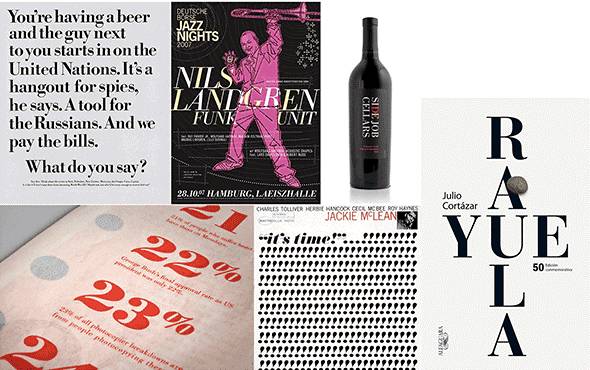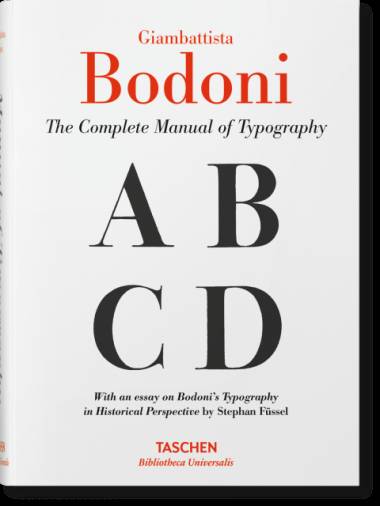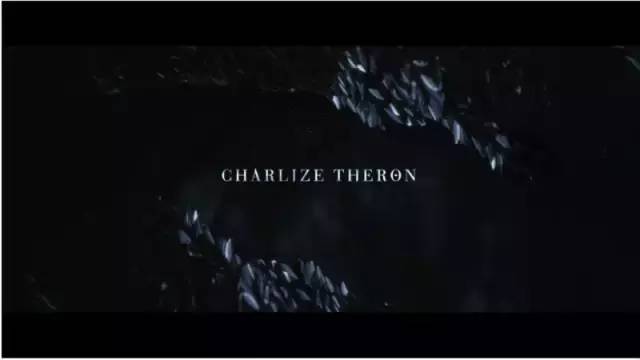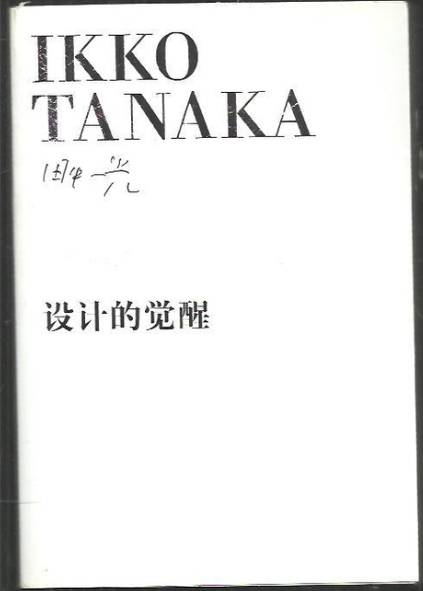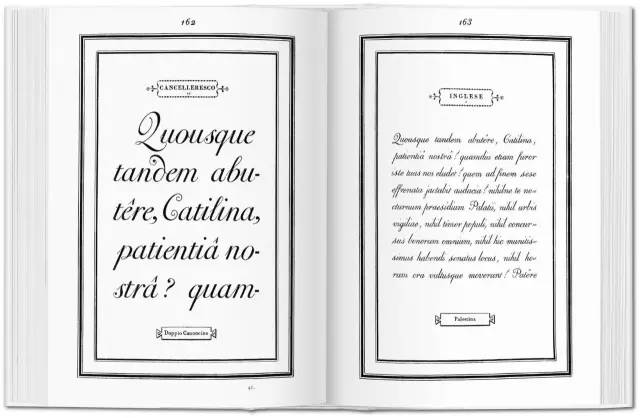
字体之美 | Bodoni字体,平面上的王者印刷
{{tag.name}}法国作家伏尔泰曾说:“文字是声音的画像”,作为一项视觉元素,文字比单纯意义上的图形、色彩更具有说服力和表现力。
在现代广告设计中,文字表现出的作用是非常重要的。广告中的文字不但能够作为信息传播的载体,还可以成为广告画面中的主体图形元素。
通过这个主体形象,不但可以对消费者展示其广告商品的自身性格,而且也可以体现出广告的文化内涵。
好的文字设计离不开字体的选择,无论是汉字字体还是字母字体都一样。网络发达的今天,随处可以下载的字体包,让我们眼花缭乱。
时间能够沉淀一切,好的字体也不例外。打开字体包,看到一个个的文字、字母,如果你只是因为某种字体好看而选择它,这样的选择似乎太轻。其实每一个好的字体背后都有其发展历史,有很多被我们忽略的故事,当你知道了这些字体背后的故事,回过头来看这些字体,也许你会看到不一样的东西。
在标题、广告上,我们经常能看到一种优雅浪漫的字体。在电影《白雪公主(与猎人)》中,导演也选择了这种字体并做了变形,他们在柔美字体的笔锋、转角、笔画交叉以及一些细节的地方加入硬朗的边缘。这就是Bodoni字体
【《白雪公主与猎人》Bodoni字体设计】
关于Bodoni字体的诞生,要从1740年意大利西北部的萨尔佐说起,那年我们的主人公金姆巴堤斯塔•波多尼(Giovanni Battista Bodoni)出生了。受印刷技术工人的父亲的影响,波多尼从小便接触印刷,十八岁时便离家到罗马教廷(教堂附设印刷厂)内当学徒。由于波多尼个性开朗,在厂内很有人缘,印刷厂主管路格里十分喜欢他,教了他许多印刷技术。在这儿,教宗希古斯兹斯五世所铸造的东方语文活字一直被荒废著不用。路格里要波多尼氏把这些活字再翻造一批。由于这次的工作经验,使他对制造活字和外国语文发生了浓厚的兴趣。
1766年,波多尼已经习得相当不错的技术,于是他离开罗马想到英国寻求发展。正当他要出发去英国时,一项工作改变了他的一生。巴尔曼的公爵费南度想设立一个印刷厂,希望波多尼到印刷厂工作,他接受了这份工作,职位是主管,此时波多尼才二十八岁。在印刷厂,波多尼负责印刷巴尔曼宫廷需要的印刷品以及费南度个人的印刷物(他是个艺术爱好者)。
波多尼的印刷厂也逐渐成为观光胜地。英国著名农业学家亚瑟·杨格在《意大利纪行》中记载著:“(1789年12月9日)下午,前往有名的波多尼印刷厂。波多尼将多数精美的印刷品展示在眼前。他的活字似乎足以凌驾巴黎的狄托氏(Didot)之上。他们两人的作风相彷,简直像为了节省纸张似的,字印得十分密集。《塔夫内与克洛耶》、《阿敏达》都印得相当精美。这些作品可以算是意大利印刷的代表,我买下后者。”
1790年以后,波多尼在巴尔曼宫廷的地位大为改善,原因是教廷驻西班牙公使准备在当地设立印刷厂以印制古典作品,邀请波多尼前往主持。此后,波多尼的印刷厂规模扩大了,而且拥有更大的自由。波多尼不仅印刷了意大利文、希腊文、拉丁文的书,更扩大到法文、俄文、德文和英文的书籍。
这时,波多尼的名声已渐渐传播到各地,所谓“王之印刷人,印刷人之王”便足以说明他的地位。不仅西班牙国王赏赐奖金,教宗也亲自颁奖给他;巴尔曼市为他铸造纪念牌,拿破伦也赏予奖金……。
一生致力于出版制作精美限量版艺术图书的著名出版商佛朗哥·玛丽亚·里奇曾说:“我清楚地记得是在1963年帕尔马的图书馆,我发现了一本古老的印刷手册,上面用的是波多尼字体,美得无以附加。于是一年后,我成立了自己的出版社,用优雅的波多尼字体印刷书籍,然后还出过一本用我自己首字母命名!
波多尼的工作大约可分两期。前期是使用旧有字体或过渡期活字的时代,这时候也大量使用装饰花纹。他显然受到法国很深的影响。1771年的活字样本簿标题页的花边就是模仿富尼尔所设计的作品。法国风味的印刷物在波多尼早期作品中随处可见,代表作有阿那克里翁的《抒情诗》等杰作。
后期所印制的书在整体概念上已富有独创性,更多的使用自己设计的字体,并避免使用装饰花纹。字体天地余白都留得相当大。在文字方面,b、d、f的头部,p、g、y的脚部刻意拉长,他它们更加明显易认。此外,在大型活字中更巧妙的嵌上小活字;如此用心设计,以求抒解字体的呆板。后期的印刷物也可以说是他的十九世纪作品,代表性的有希腊文《伊里亚特》(三卷)、费内隆(Fenelon) 的《忒勒马克斯》等。
1790年诞生的Bodoni字体经历了数百年的时间考验依旧是那样的经典,在欧洲最大的专业字体设计公司fontshop公布的世界上100个最佳字体中Bodoni 排名第4。
【田中一光的《设计的觉醒》封面英文使用Bodoni字体】
TASCEHN出版的《GiambattistaBodoni Manual of Typography》一书中,收集了波多尼设计的十分惊人的语言文字种类。全书752页,除了常见的罗马字母、德语和俄语,还有鞑靼文、叙利亚字母、希伯来文、埃塞俄比亚的吉兹文、亚美尼亚字母、伊特鲁里亚字母、腓尼基字母、布匿字母、伊利里亚文、藏文、古埃及文、天城文、格鲁吉亚字母等。此外还有数量庞大的花边、题头、装饰图案,甚至四线谱和五线谱的音乐符号也没有遗漏。